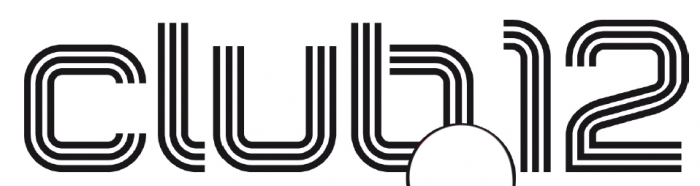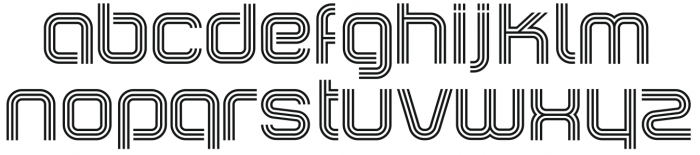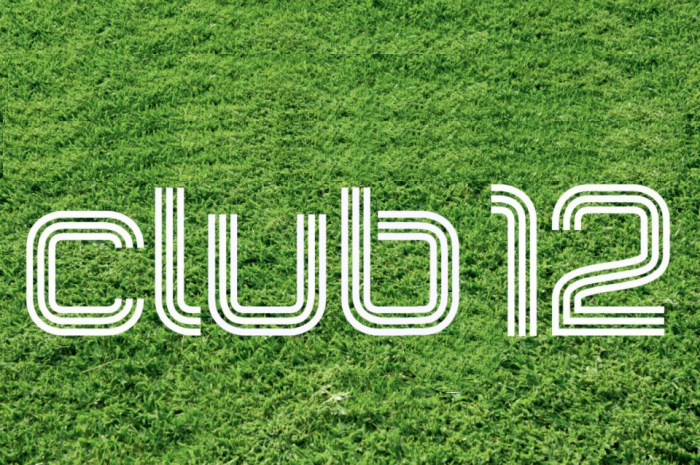
Fussball Schrift Dreilinie
Weiss jemand wie die Schrift  heisst? (siehe Datei)
Es ist nicht die pump triline und trisect....
der eher schlechten technischen Umsetzung (links unten im b, rechts Mitte bei der 2) nach schließe ich eher auf handgebastelt und weniger auf einen Font. Aber vielleicht wissen die Luzerner Kicker mehr … ;-)
Der Vereinsvorstand E.W. verwendet das Logo in pdfs, da sieht es weniger verbastelt aus. Vielleicht hat er ja die Vektordaten.
da hast du natürlich recht, das ich die Kickers Jungs fragen könnte... wenn ich das täte ginge die Überraschung leider verloren, wohl oder übel muss ich den Mani trotzdem fragen...
Du könntest den Schriftzug in Illustrator, CorelDraw oder einem anderen Vektorprogramm auf Basis einer ähnlichen Schrift erstellen und die Dreifachlinie zuweisen. Das wäre wahrscheinlich die einfachste Lösung. Oder du schaust noch bei dafont.com …
Was genau wird denn gebraucht? Genau nur das Logo:
oder einen ganzen Font:
(das ist hier allerdings noch keiner, bislang nämlich nur mal eben schnell mit Corel gezeichnet)
Könnte es sein, dass diese Buchstaben einer älteren Adidas-Trikot-Beschriftung entstammen?
Egal, meine habe ich noch um einiges erweitert, und würde gern Eure Meinung dazu erfahren: